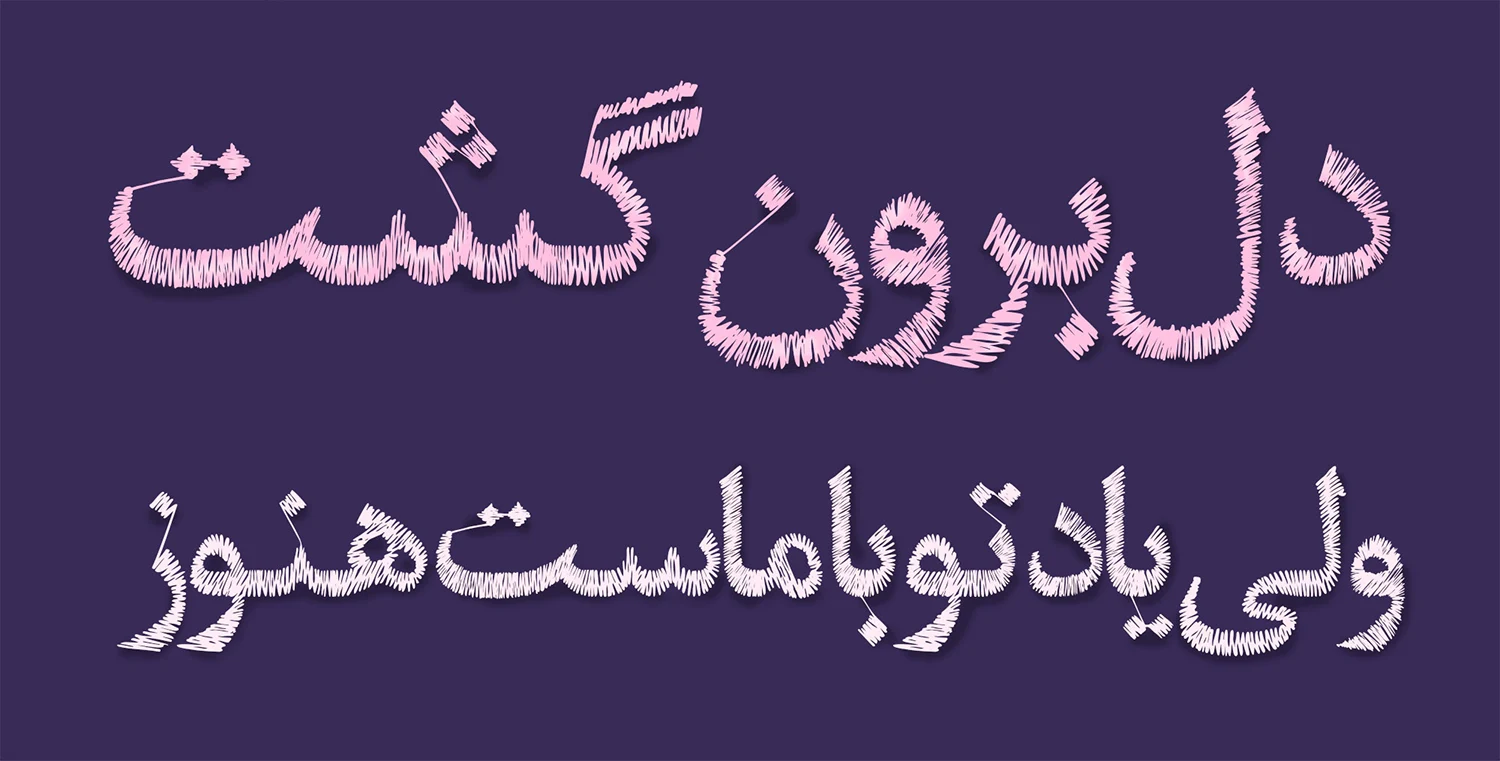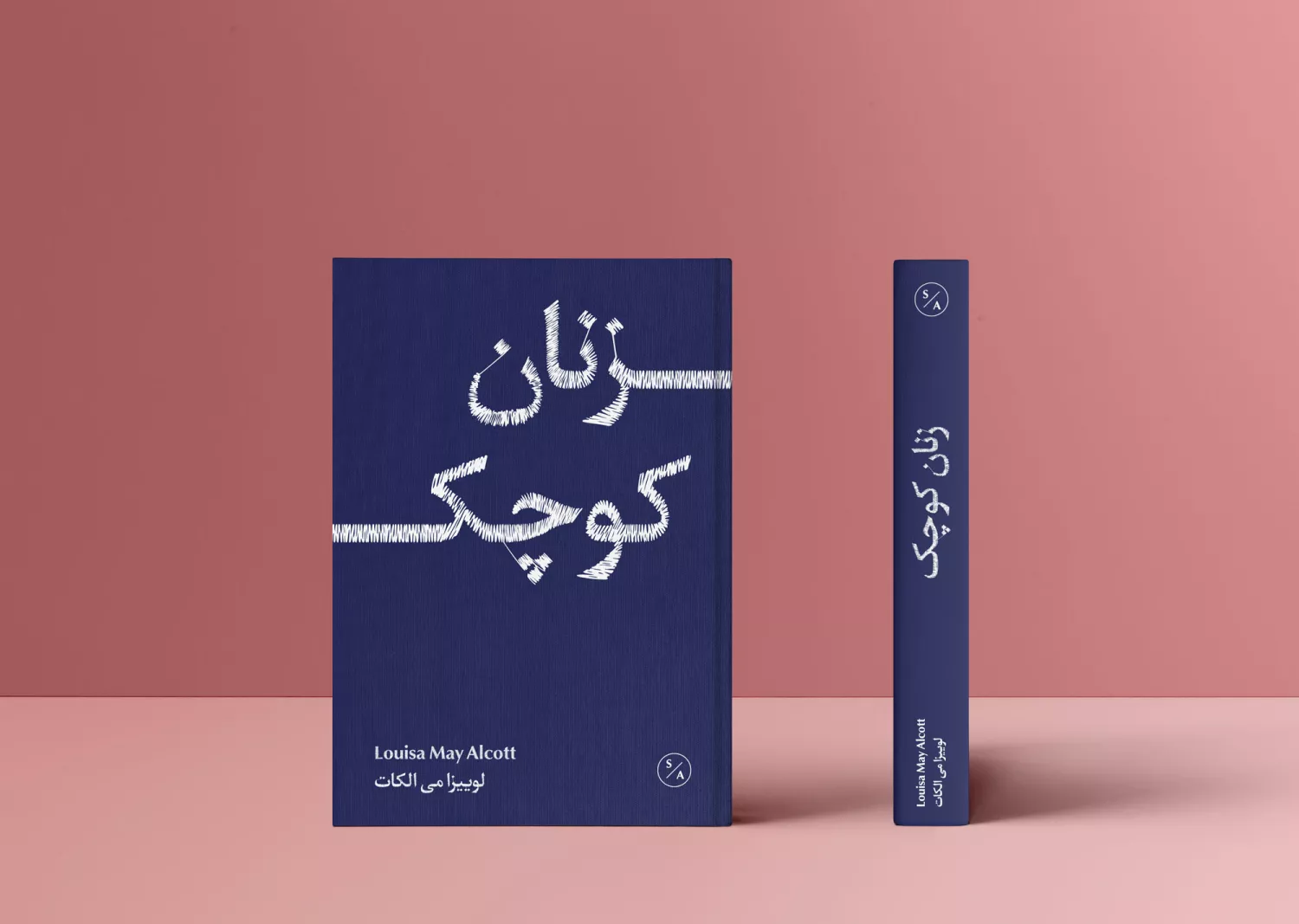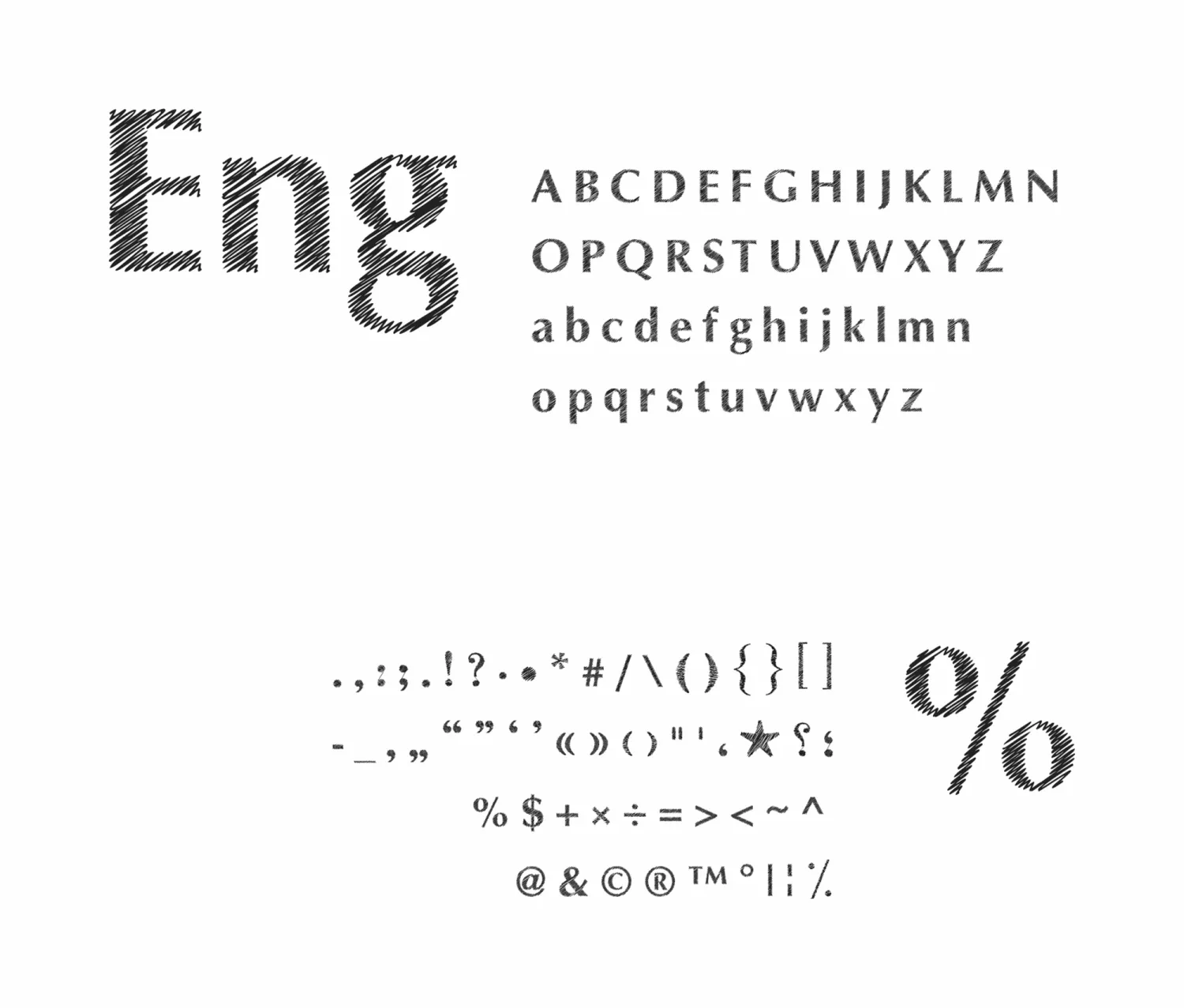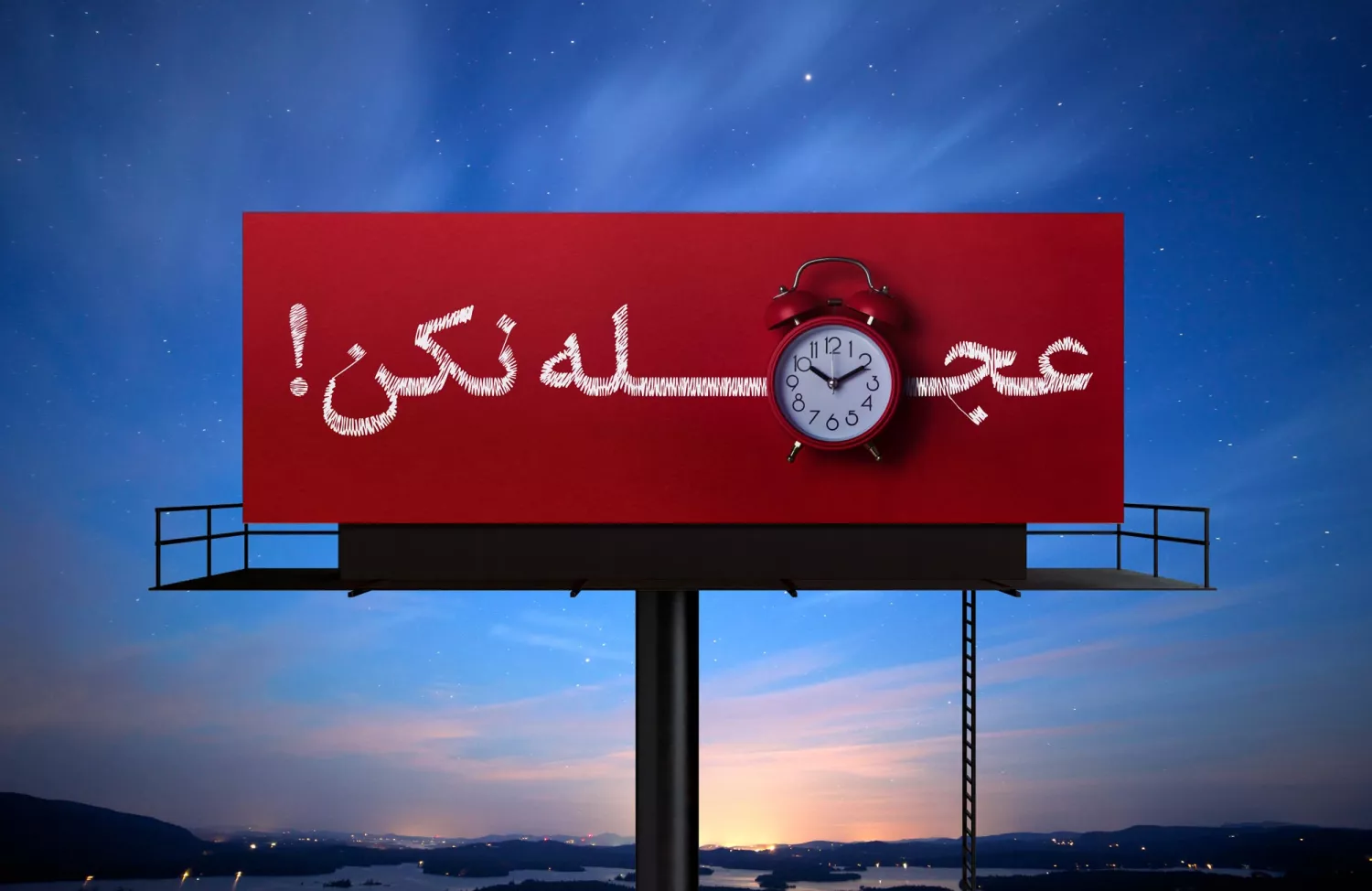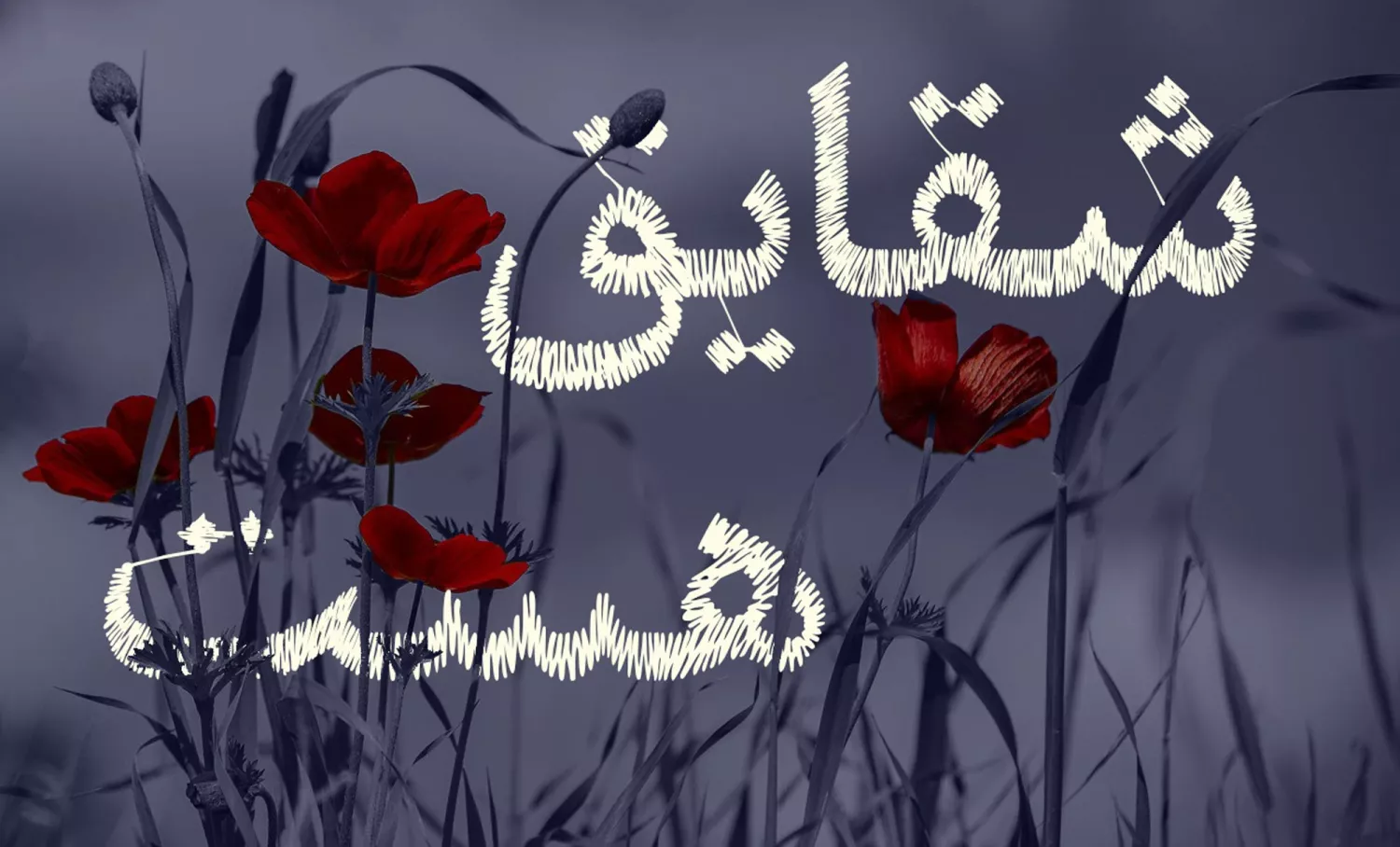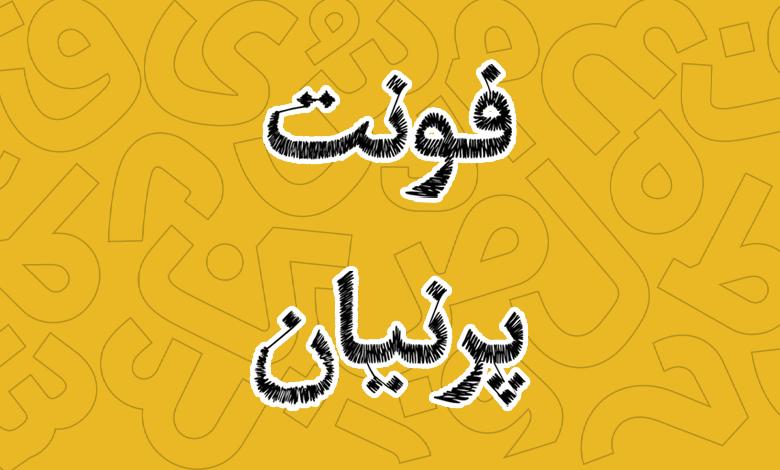
فونت پرنیان (Parnian)
فونت پرنیان (به انگلیسی: Parnian) یکی دیگر از فونتهای فانتزی و در دسته قلمهای نمایشی است که با اهام از قلم نازنین ساخته شده است. خصیصه متفاوت دیگر این قلم این است که فونت با استفاده از خطوط گلدوزی شده طراحی شده است که چنین طرحهایی پیش از ایجاد قلم پرنیان، به صورت دستی در نرمافزارهای گرافیکی در یک فرآیند سخت به منظور استفاده در فضای تبلیغاتی مورد استفاده قرار میگرفتند.
این فونت توسط پرنیان کاشفی در قالب یک پروژه دانشجویی در کارگاه طراحی تایپفیس ایجاد شده است. روند طراحی نیز بهاین شکل بوده که تمامی حروف و کلمات در این قلم ابتدا روی کاغذ پیادهسازی شده و سپس با عکاسی و انتقال به نرمافزارهای ساخت فونت به این نسخه نهایی تبدیل شده است.
بعدها به منظور فراهم کردن این قلم برای استفاده عمومی، یک سری اصلاحات نرمافزاری روی این قلم توسط شهرزاد اکبری صورت گرفته و نسخه پایانی این فونت شده است که میتوانید با دانلود و نصب آن، در طراحی پوستر، جلد کتاب، بیلبورد و پست شبکههای اجتماعی نگاهی متفاوتتر را در اختیار مخاطبان خود قرار دهید.
تمامی حروف در تمامی زبانهای قلم پرنیان، با استفاده از خطوط هاشوری گلدوزی شده طراحی شده است که حروف دارای نقطه درست مانند طرحهای گلدوزی به منظور برش نخوردن نخ و جدا نیفتادن از حروف، نقاط با یک خط به حروف متصل شدهاند. چه برای نقاط تکی و چه چندتایی؛
فونت فارسی نمایشی الهام گرفته از گلدوزی
در این قلم فارسی همانطور که در تصویر بالا میبینید، کلیه حروف روی کاغذ به صورت دستی پیادهسازی شده و سپس از طریق عکاسی به نرمافزار برای ایجاد گلیفهای فونت منتقل شدهاند. طراحی چنین فونتی از این نظر نیاز به صرف زمان و انرژی بسیار زیادی دارد.
پشتیبانی از زبان عربی و انگلیسی
فونت فارسی پرنیان، از دو زبان دیگر هم پشتیبانی میکند. زبان اول عربی است که بر پایه همان رسم خط فارسی است. در این زبان کلیه حروف فارسی که به صورت مشترک در عربی مورد استفاده قرار میگیرند در فونت جای گرفته است. اما علاوه بر آن حروف دیگری مثل «ک، ی، ه، ؤ، ئ» که ساختاری متفاوت از زبان فارسی دارند برای این زبان نیز پیاده سازی شده است.
نکته بعدی که در مورد تفاوت نسخه فارسی و عربی فونت پرنیان وجود دارد، تنوین و اعرابهای این قلم در هر دو زبان است. در این قلم میتوانید به صورت کامل کلمات عربی را همراه با اعراب مختص خود تایپ کنید.
زبان دیگری هم که قلم پرنیان از آن پشتیبانی میکند، انگلیسی است. در این زبان لاتین هم کلیه حروف انگلیسی و کاراکترهای خاص این زبان نیز با همان طرح گلدوزی شده از خطوط مورب پیاده سازی شده است تا برای استفاده در متنهای چند زبانه نیاز نباشد به دنبال فونت دیگری باشید؛ چرا این که فونت خاص بوده و در سایر زبانها چنین سبک قلمی وجود ندارد.
این قلم جدای از اعداد و حروف، از تمامی سنبلها مطالب هر زبان پشتیبانی میکند. برای مثال نمادهای گیومه که در زبان انگلیسی با فارسی ساختاری برعکس دارند در این فونت روی آن کار شده است.
پشتیبانی از اعداد فارسی و لاتین
ویژگی دیگر فونت پرنیان پشتیبانی از اعداد فارسی است. در این قلم کلیه اعداد در هر سه زبان متناسب با نسخه خود طراحی شده است تا در طراحیهایی که انجام میدهید، برای هر زبان استانداردها رعایت شده باشد.
کلیه اعداد، عملگرهای ریاضی، کاراکترهای خاص و سنبلها در هر زبان که مشترک هستند پیاده سازی شده و برای سایز زبانها هم اگر تفاوتی وجود دارد یا شکل کلی آنها متفاوت است، درنظر گرفته شده است.
مناسب برای تبلیغات و فضای نمایشی
پر کاربردترین استفادهای که میتوان برای قلم پرنیان داشت در فضاهای نمایشی و تبلیغاتی است. از این قلم میتوانید در ساخت انواع بیلبورد شهری، بنر و اسلایدر در سایت و شبکههای اجتماعی، صنعت چاپ همچون طراحی جلد کتب و حتی صنایع بستهبندی در حوزه محصولاتی که مرتبط با کالای خواب و پارچه هستند استفاده کنید.
چرا که این فونت از طراحی گلدوزی (نخ، سوزن و پارچه) الهام گرفته شده است و برای همین جهت میتواند در همین حوزه، بهترین اثرگذاری را روی ذهن مخاطب داشته باشد. بهویژه در بحث تبلیغات برای چنین محصولاتی که خود ایجاد یک حس آرامشخاطر را بهدنبال خواهد داشت.
این فونت هرچه در ابعاد بزرگتر مورد استفاده قرار گیرد که خطوط هاشور خورده گلدوزی حروف بهتر دیده شوند، خود را بهتر نمایش خواهد داد که ساختاری دوستانه و نرم دارد.
جدیدترین نسخه فونت پرنیان همان ورژن ۱.۰ است که در آذر ۱۴۰۱ منتشر گردیده است. این فونت که پیش از این یک پروژه دانشجویی در کارگاه طراحی فونت فارسی بود، بعد از رفع برخی نواقص اصلاحات نرمافزاری روی آن انجام گرفته و برای استفاده عمومی منتشر گردید.